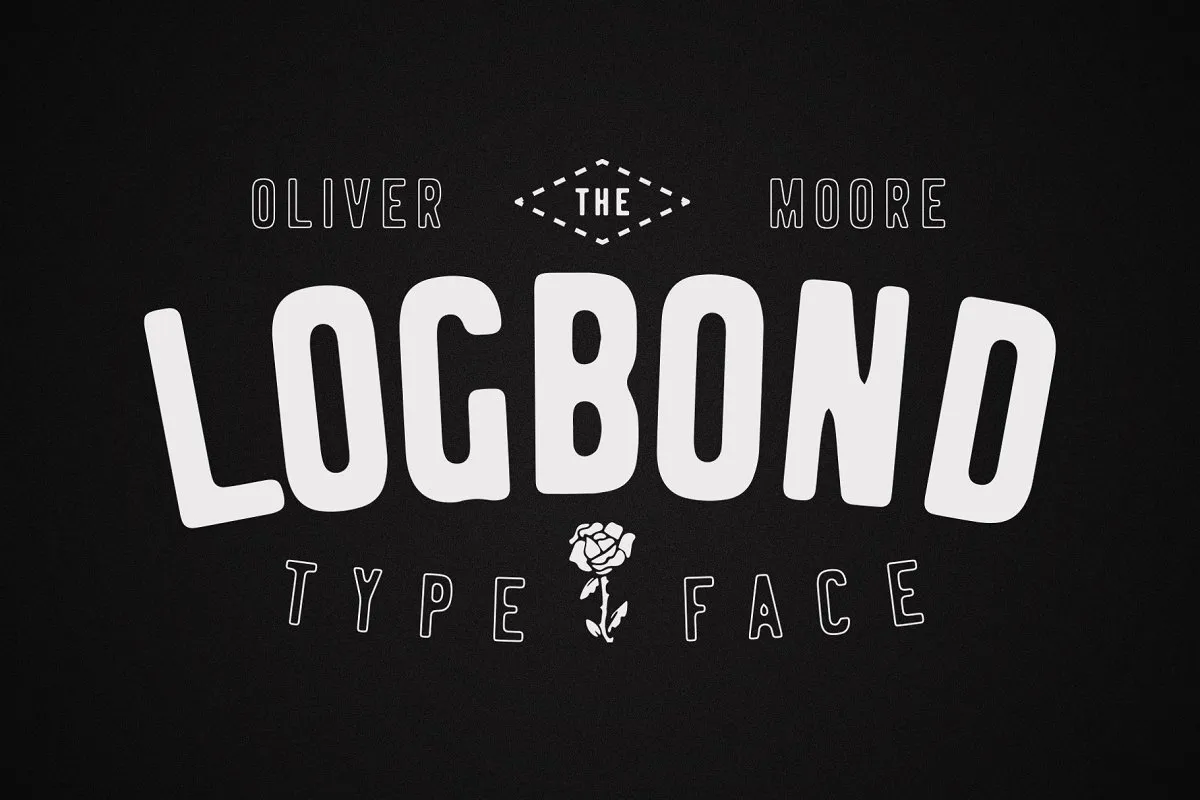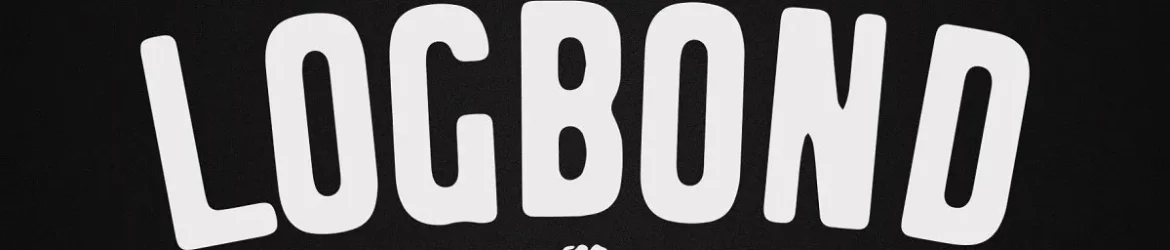
Introduzimos a Logbond Typeface, uma fonte premium criada por Oliver Moore disponível para download gratuitamente no Creativemarket. Esta é uma escolha inteligente para designers que buscam uma fonte de estilo display com um ar vintage. A Logbond é uma fonte condensada e alta, conhecida por seu efeito especial da assinatura que cria um clima nostálgico em projetos de design. Seja para trabalhos tipográficos, impressões ou até mesmo estampas em tatuagens, a família de tipo Logbond oferecerá uma experiência única e envolvente, criando um toque especial no seu projeto. Esse é o momento ideal para experimentar essa fonte excepcionalmente elegante gratuitamente.